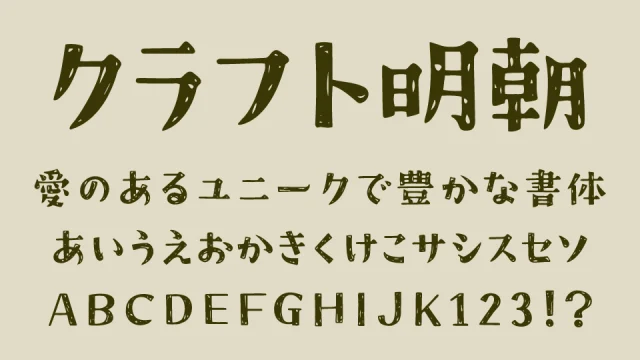
オシャレ「Vlog」にぴったりな日本語フリーフォント
今回は、YoutubeやTiktokでも人気あるジャンル「Vlog」にぴったりな日本語フリーフォントをまとめてみました。
「Vlog」は、モーニングルーティン、旅行動画、休日の様子、など記録している動画で、YoutubeやTiktokを中心に人気を博している動画ジャンルです。「Vlog」はオシャレな動画に仕上げることが多く、そんなオシャレな雰囲気がでる「Vlog」にぴったりなフリーフォントをご紹介します。
「Vlog」におすすめな日本語フリーフォントまとめ
クラフト明朝
クラフト明朝フォントは、手書きのようなグシャグシャに塗りつぶしたかすれがオシャレで可愛らしいデザインの明朝体です。
手書きっぽい質感が、Vlog動画との相性が良いフォントです。
ヒカリノカナ
FGPヒカリノカナ荒フォントは、上下に飛びているユニークな動きがある半角カナ文字のようなフォントです。
文字の形も特徴的で、ザラザラとした質感もオシャレ感をアップさせるVlog動画にぴったりなフォントです。
黒薔薇ゴシック
黒薔薇ゴシックは、フリーフォントのゴシック体M+ FONTSから派生フォントとして、文字にトゲトゲの装飾が施されたデザインフォントです。
トゲの装飾が付いていることで、オシャレ&クールな雰囲気を作れるフォントです。
セリフゴシック
AFSセリフゴシックフォントは、文字先にどっしりとしたセリフ装飾が付けられているデザインゴシック体のフォントです。
ZEN紅道
ZEN紅道(Zen Kurenaido)フォントは、手書きのような文字と活字らしさを感じるデザインフォントです。
手書きっぽさがあることで、手作りした親近感が表現できるフォントです。
Murecho
牟礼町(Murecho)フォントは、ジョージアを拠点とするデザイナーNeil Summerour氏によるゴシック対フォントです。
ゴシック体でしっかりと視認性が高いフォントながら、ちょっとした丸みがあることで、柔らかい雰囲気を作り出せるフォントです。
FGUI源
FGUI源フォントは、長体(コンデンス)にデザインされている仮名文字と、漢字が組み合わさることで、文章がリズミカルな雰囲気を感じるフォントとなっています。
Vlog動画のテロップなどにちょっとしたアクセントをつけたい場面におすすめです。
一樹令和
KazukiReiwa(一樹令和)フォントは、墨溜まり加工が施されている上品で、柔らかい印象をもつオールドスタイルの明朝体フォントです。
大人っぽいオシャレな雰囲気を作りたいVlog動画にぴったりなフォントです。
流線形
流線形フォントは、源ノ明朝フォントをベースに、7°の傾斜と文字先を丸く調整された明朝体フォントです。
築豊明朝
築豊明朝フォント(つくほうみんちょう)は、伝統的な本文向け明朝体を意識して作られたかな書体となっています。
古風な雰囲気をもつので、日本旅・神社寺院巡りなどの日本旅Vlogにぴったっりなフォントです。
にくまるフォントは、ゆるくて、やさしく、柔らかい雰囲気が特徴のデザインフォントです。まるまるっと太ったフォルムは愛らしく可愛らしいデザインになっています。
えるまー
えるまーフォントは、丸みのあるクレヨンやマジックペンで書いたような手書きフォントです。手書きフォントながら太めでインパクトあるので、子供っぽい元気な雰囲気を作りたい場面などにぴったりなフォントです。
推しゴフォントは、推し活グッズ制作を目的に作られたフォントで太さもあり、遠くからの見えやすさにこだわって作られたゴシック体フォントです。